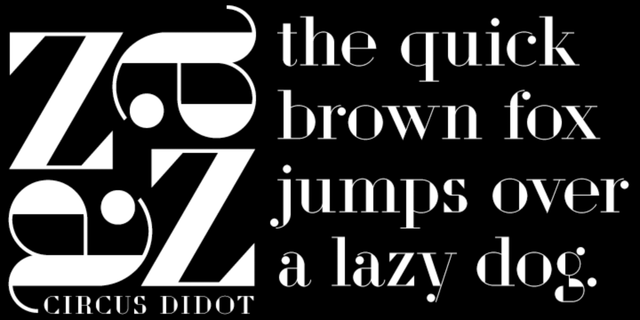
Шрифт Circus Didot (Циркус Дидо) представляет собой конструктивистскую переработку модели классицистической антиквы. Анализируя формы знаков, автор размещал по шаблону контура базовые геометрические формы — треугольники, прямоугольники, окружности… Полученные конструкции, продолжая оставаться знаками антиквенного шрифта, в то же время напоминали работы русских авангардистов 20-х годов прошлого века. Это неожиданное открытие натолкнуло на мысль сделать дизайн, в котором стремление новостильной антиквы к рациональности и геометрии доведено до максимума. За основу был взят шрифт Дидо и реализован в стиле конструктивизма, подчеркивающем геометрию структурных компонентов знаков в их супрематическом совершенстве. В процессе работы, помимо антиквы нового стиля, использовались идеи рисованных шрифтов авангардистов и стиля ар-деко. Эквилибристика и фокусы с преобразованием форм объясняют название проекта. Шрифт спроектирован молодым московским дизайнером Данилой Орловским. Выпущен компанией ПараТайп в 2010 году.